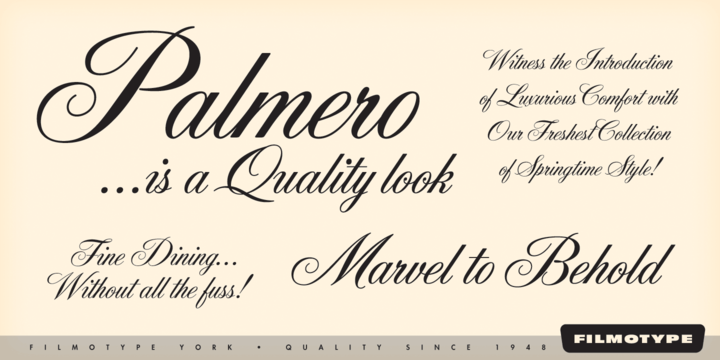
Filmotype York Font
A Filmotype York é uma elegante fonte tipográfica que surgiu no final dos anos 1950 e foi projetada para estabelecer a categoria de letra formal script da Filmotype. Especificamente criada como uma fonte de corte de chumbo, essa letra é perfeita para ocasiões formais como convites de casamento ou cerimônias de grande importância. Suas linhas equilibradas garantem que a fonte seja tanto visualmente atraente quanto levemente legível mesmo quando utilizada em tamanhos menores, tornando-a perfeita para uso em eventos formais e ocasões especiais. A Hamilton foi responsável por projetar essa fonte elegante, oferecendo uma opção única e sofisticada para aqueles que buscam um toque de formalidade na sua próxima impressão criativa ou tradicional.